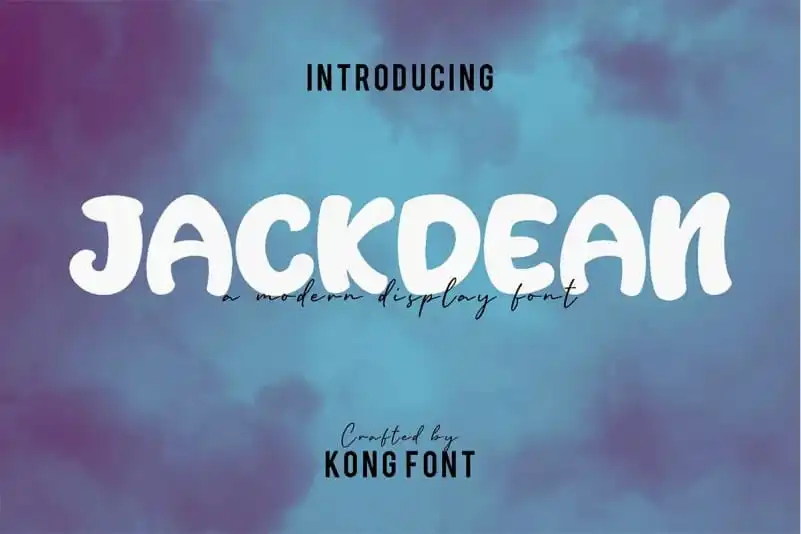
Jackdean Display Font – Download Grátis
A fonte Jackdean Display Font foi criada a partir das ideias de escrita à mão aplicadas ao tipo. Esta coleção de scripts é perfeita para personal branding. O designer desta font foi fontkong, um nome respeitado na comunidade do design digital. A Jackdean Display Font inclui uma grande variedade de caracteres alfabéticos e numéricos, assim como pontuação, tudo isso disponível em um único arquivo compacto que é excelente para diversos tipos de uso. Seja para invitações, logotipos, rótulos ou até mesmo as monogramas e letrinhas à mão, esta font oferece uma escolha incrível de design e personalização. Suas linhas sofisticadas e acentos elegantes criam um efeito visual que chama atenção e permite expressar sua marca de maneira única. Ideal para quem busca transmitir seu estilo no ambiente digital ou impresso, Jackdean Display Font é uma escolha ótima para designers gráficos, profissionais digitais ou até mesmo pessoas amadoras que desejam criar algo especial em seus trabalhos. A Jackdean Display Font oferece mais do que apenas aparência. Suas características únicas permitem que você personalize seu design ao máximo, criando identidades visuais memoráveis que se destacam e permanecem como uma marca duradoura para sua empresa ou projeto pessoal. Engane-se se pensar que a fonte Jackdean Display é simplesmente um recurso visual; ela é também uma ferramenta poderosa de design que pode ajudá-lo a expressar sua identidade única através do uso da linguagem gráfica em seu próprio jeito.